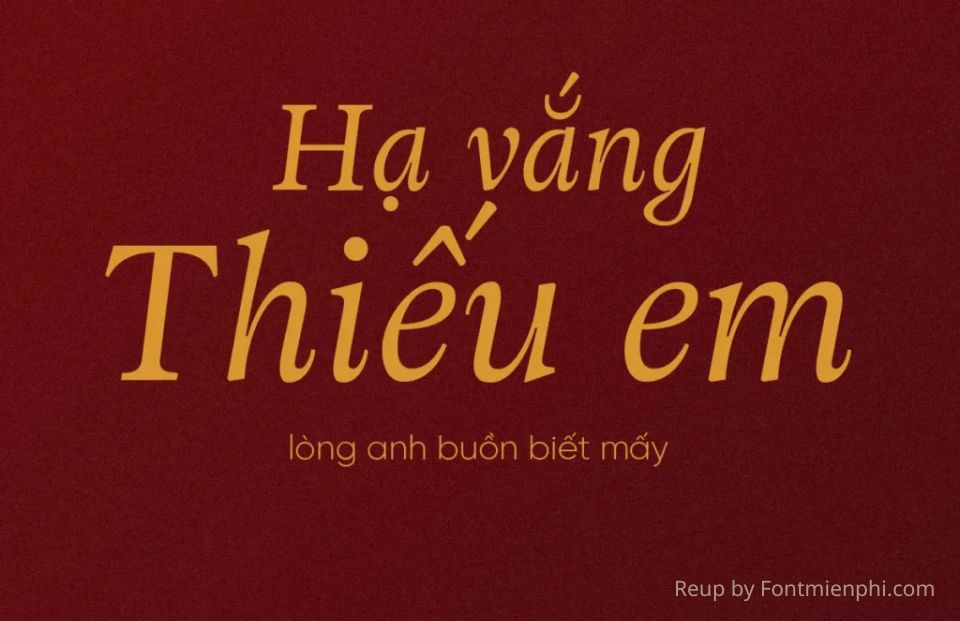
Đây là một phông chữ có chân (serif) mang phong cách thanh lịch, đề cao tính dễ đọc và có tính ứng dụng cực cao trong lĩnh vực dàn trang sách, báo hay tạp chí. Với thiết kế cân đối kết hợp cùng các chi tiết serif mềm mại, VL Adriane Swash mang đến cho người xem cảm giác chuyên nghiệp, pha trộn hoàn hảo giữa nét cổ điển và hơi thở hiện đại.
Đặc biệt, phiên bản đang được chia sẻ miễn phí trên Fontmienphi.com đã được Việt hoá trọn vẹn, hỗ trợ đầy đủ các dấu câu tiếng Việt. Điều này giúp văn bản hiển thị rõ ràng, đồng bộ và mượt mà, vô cùng lý tưởng cho các dự án đòi hỏi nội dung dài như tiểu thuyết, truyện chữ hay các bài biên tập chuyên sâu.
🌟 Đặc Điểm Nổi Bật Của Font VL Adriane Swash
• Tối ưu cho văn bản dài: Thiết kế serif chuẩn mực, cực kỳ dễ đọc, giúp mắt không bị mỏi khi theo dõi nội dung lớn.
• Chuyên trị dàn trang: Là lựa chọn hoàn hảo và an toàn cho việc dàn trang sách, truyện và tạp chí.
• Thẩm mỹ cao: Nét chữ toát lên sự thanh lịch, tinh tế nhưng vẫn giữ được sự chuyên nghiệp.
• Thuần Việt 100%: Hỗ trợ hiển thị chuẩn xác trọn bộ ký tự và dấu câu tiếng Việt.
• Sắc nét trên mọi nền tảng: Đảm bảo chất lượng hiển thị xuất sắc cả khi in ấn thực tế lẫn trên màn hình kỹ thuật số.
🎨 Ứng Dụng Thực Tế
• Thiết kế bìa và dàn trang sách, tiểu thuyết, truyện chữ.
• Dàn trang layout báo chí, tạp chí thời trang hoặc nghệ thuật.
• Trình bày nội dung editorial đòi hỏi chiều sâu và tính thẩm mỹ.
• In ấn tài liệu, văn bản, hồ sơ chuyên nghiệp.
• Thiết kế các ấn phẩm trích dẫn (quote) hoặc typography mang phong cách nhẹ nhàng.
• Xây dựng giao diện hoặc hình ảnh cho các trang blog mang hơi hướng hoài cổ, cổ điển.